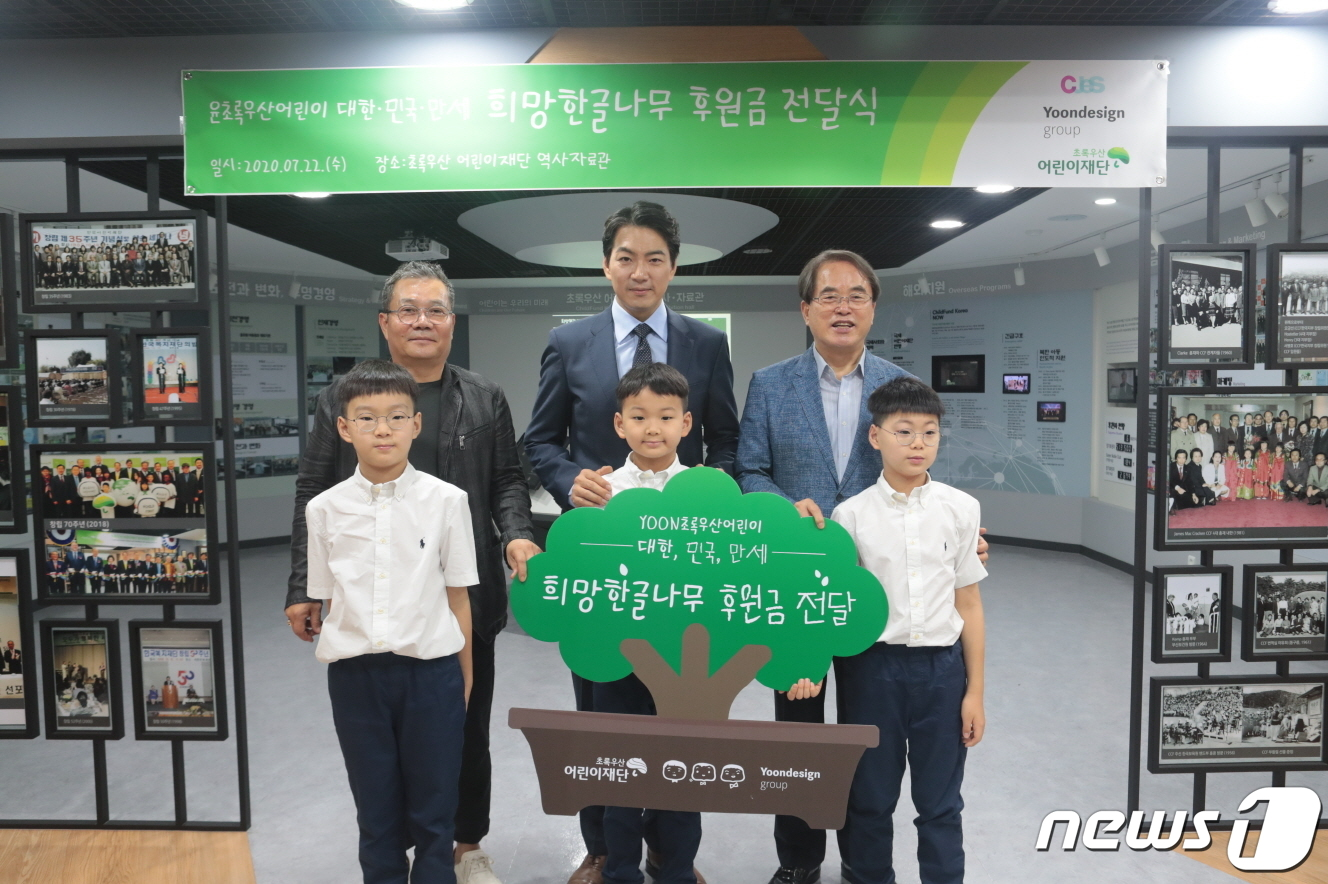
‘윤초록우산어린이 대한·민국·만세’ 희망한글나무 후원금 전달식
㈜윤디자인그룹과 '윤초록우산어린이 대한·민국·만세'의 한글나무 후원금 전달식
지난 22일 오후 서울 중구 초록우산어린이재단 2층 역사자료관에서 진행된 희망한글나무 후원금 전달식에서 관계자들이 기념촬영을 하고 있다. 초록우산 어린이체 프로젝트는 우리 사회가 아이들의 소중한 목소리에 좀 더 귀 기울이자는 취지에서 기획되었으며, 송대한·송민국·송만세 세 쌍둥이의 손글씨를 모티브로 윤디자인그룹의 전액 재능기부로 제작되었다.
삼둥이체는 소액기부를 통해 서체를 다운로드 받을 수 있는 ‘희망한글나무 캠페인’을 통해 약 365명이 일시 후원에 동참하여 수익금 250여만원이 모금되었으며, 후원금은 복지 사각지대의 소외계층 아동을 위해 쓰일 예정이다.